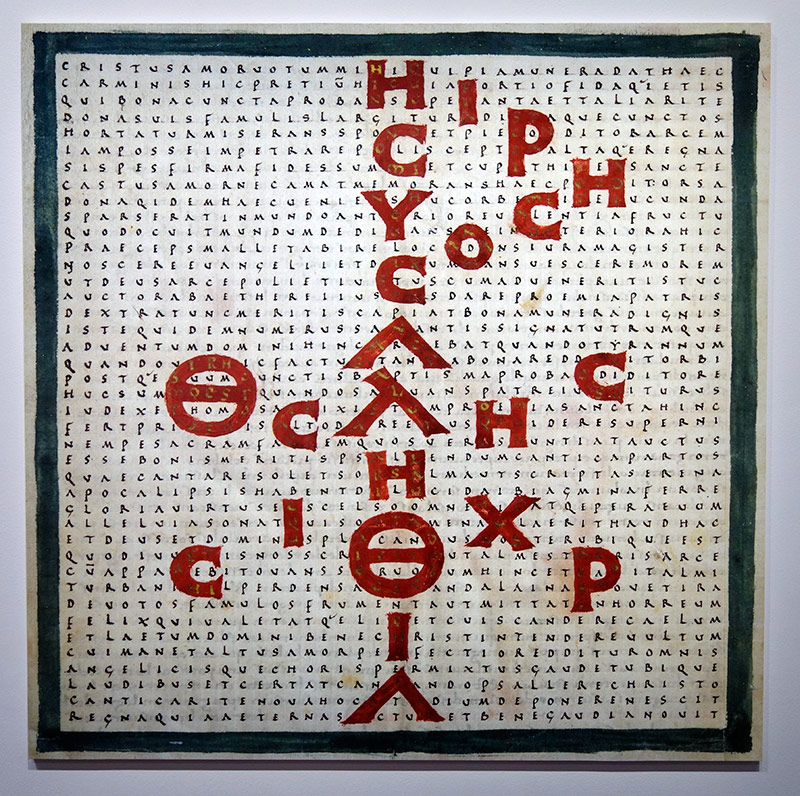
Une exposition en ce moment à la BNF autour de Raban Maur, un moine allemand de 10e siècle. On peut avoir la foi ou pas, peu importe, mais le bonhomme a mené très loin les limites de la création humaine. Dans son ouvrage Louanges de la Sainte Croix, il a imaginé des textes qui peuvent avoir jusqu'à quatre niveaux de signification et de lecture. Ainsi, sur l'image jointe à ce courriel : 1er niveau : les petites lettres qui, ligne à ligne, forment un
poème latin (pas d'espace de séparation des mots) Pour l'exposition, 5 manuscrits des Louanges, provenant
de bibliothèques différentes, ont été réunis...